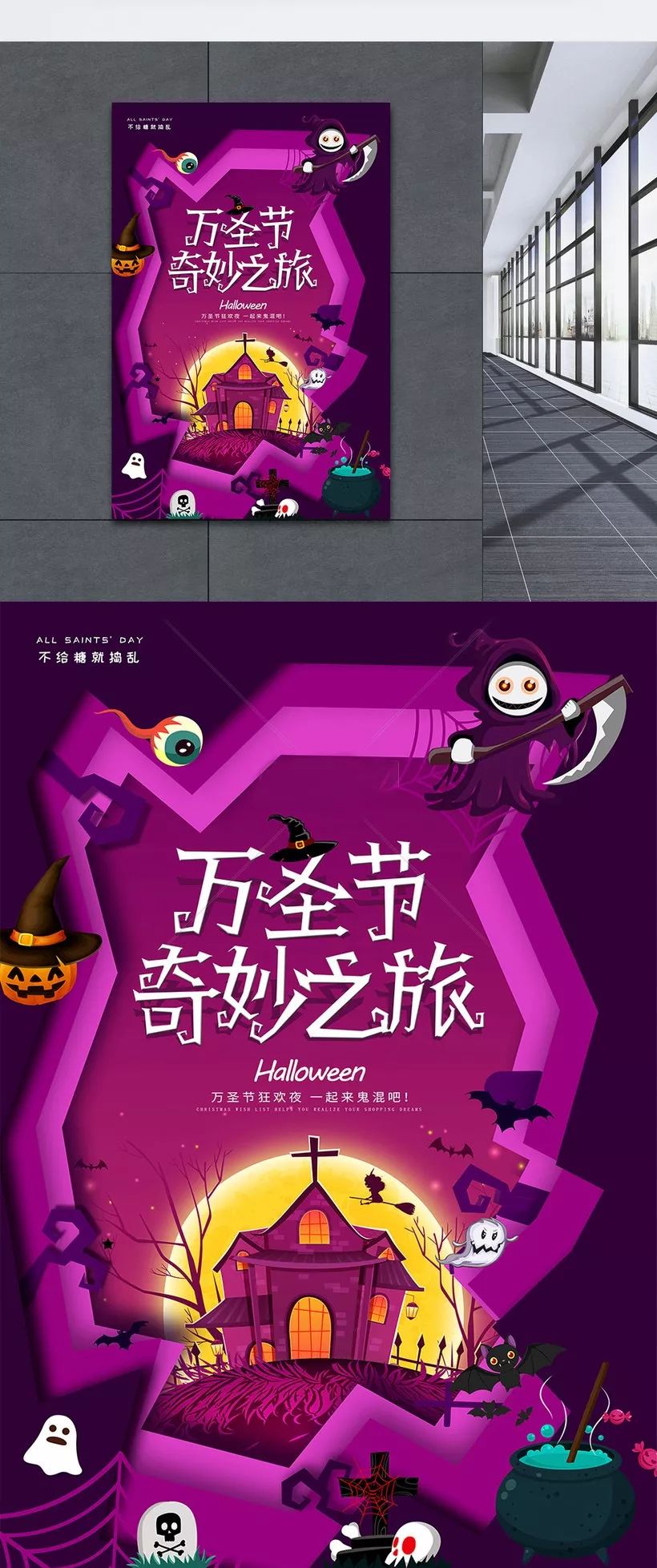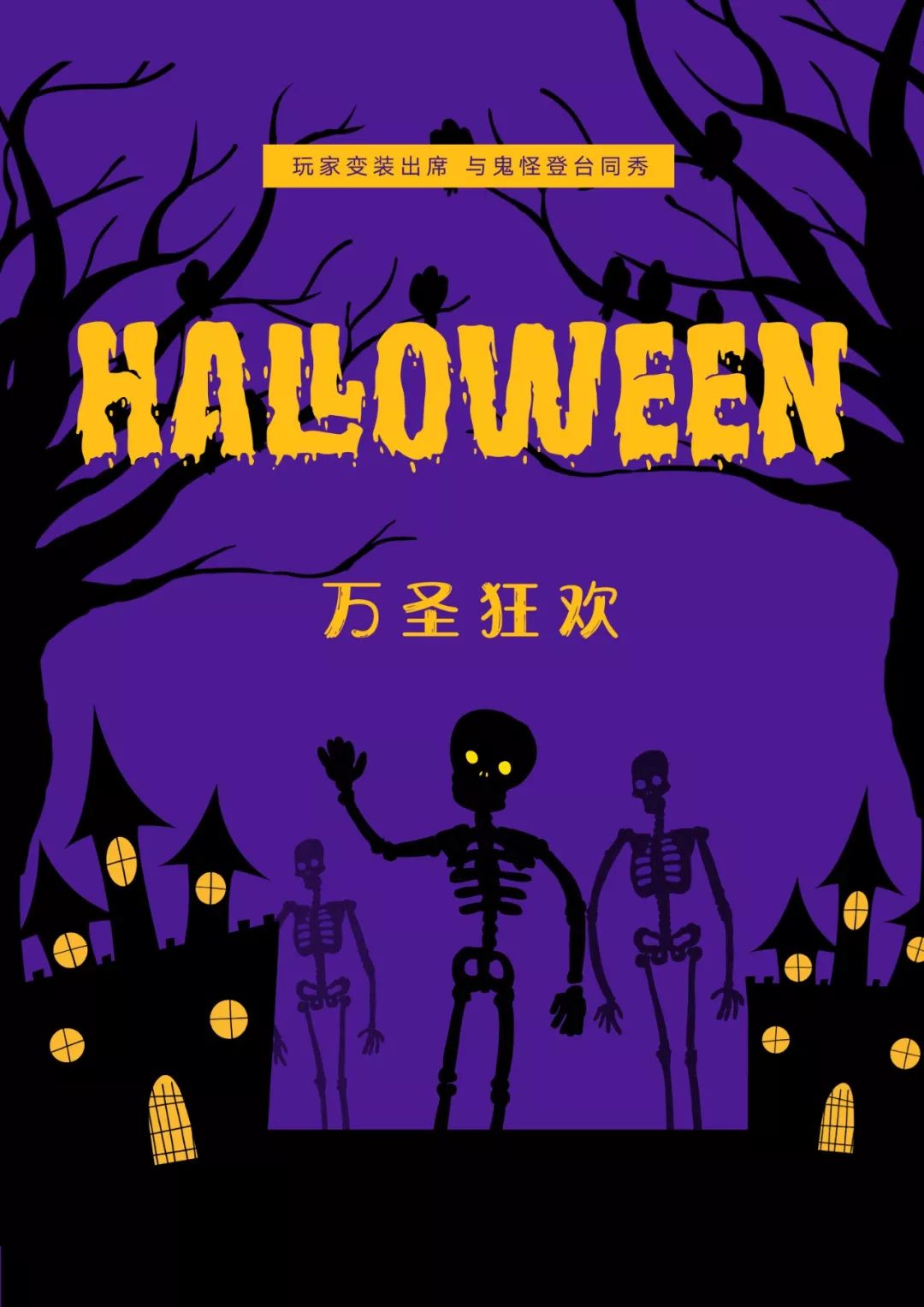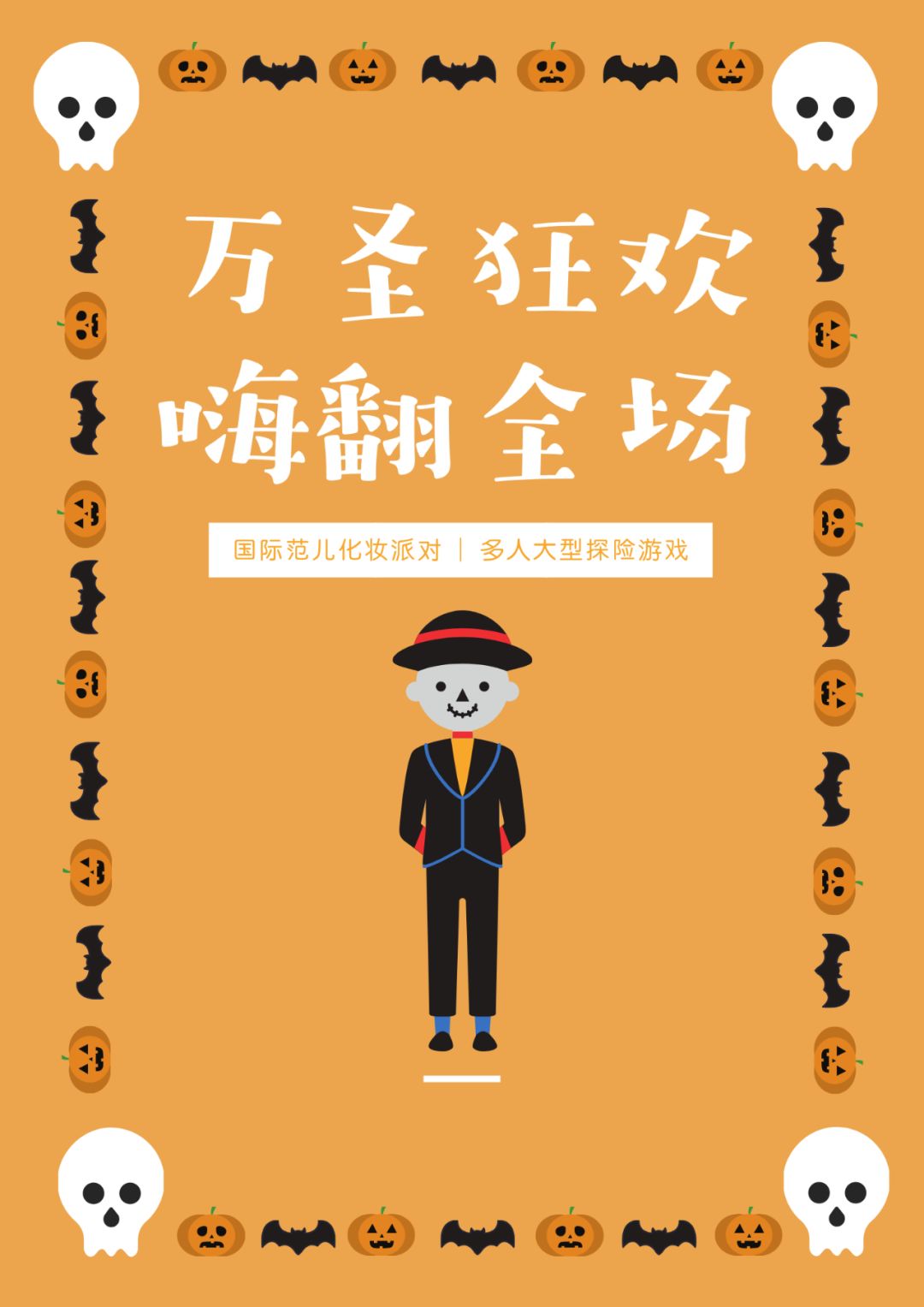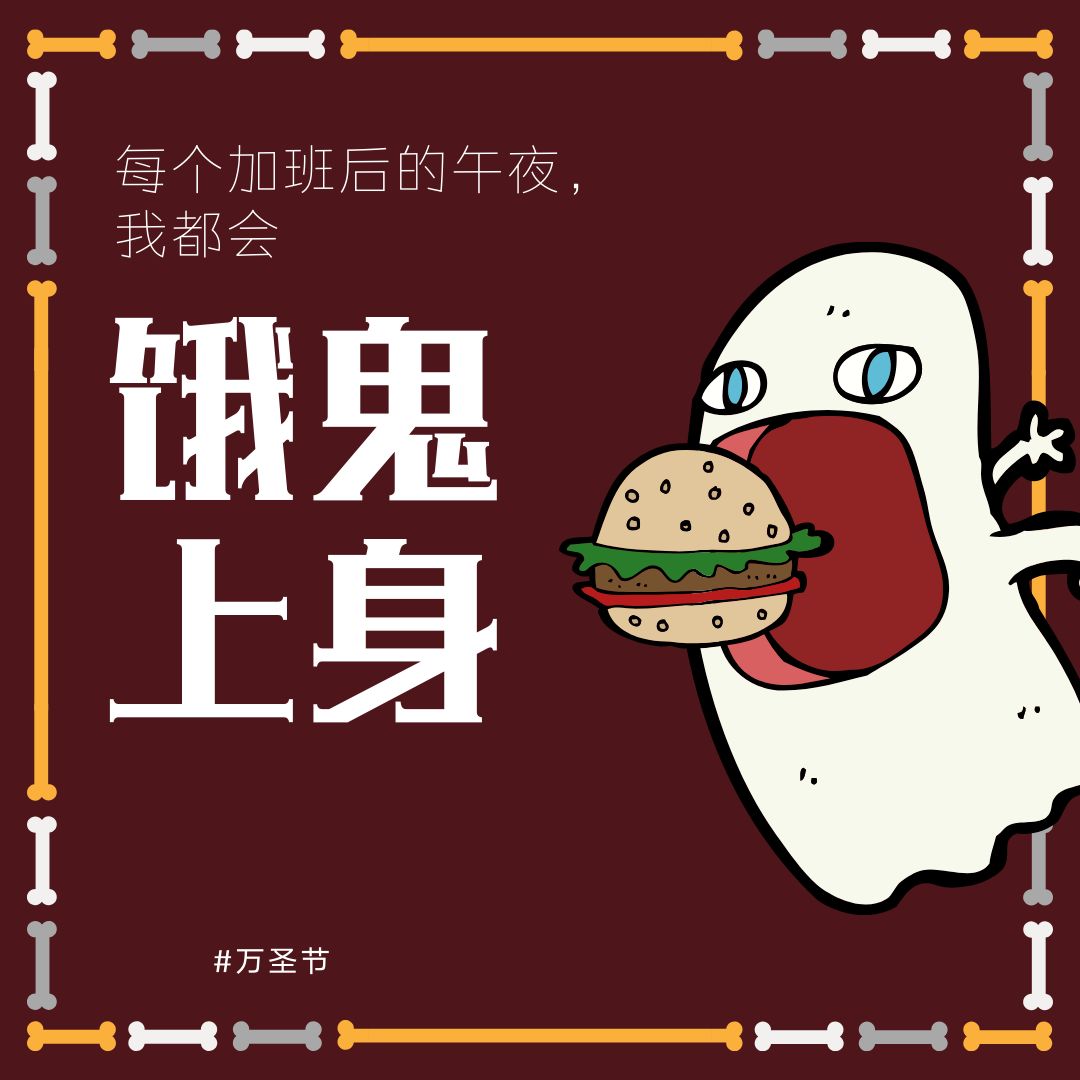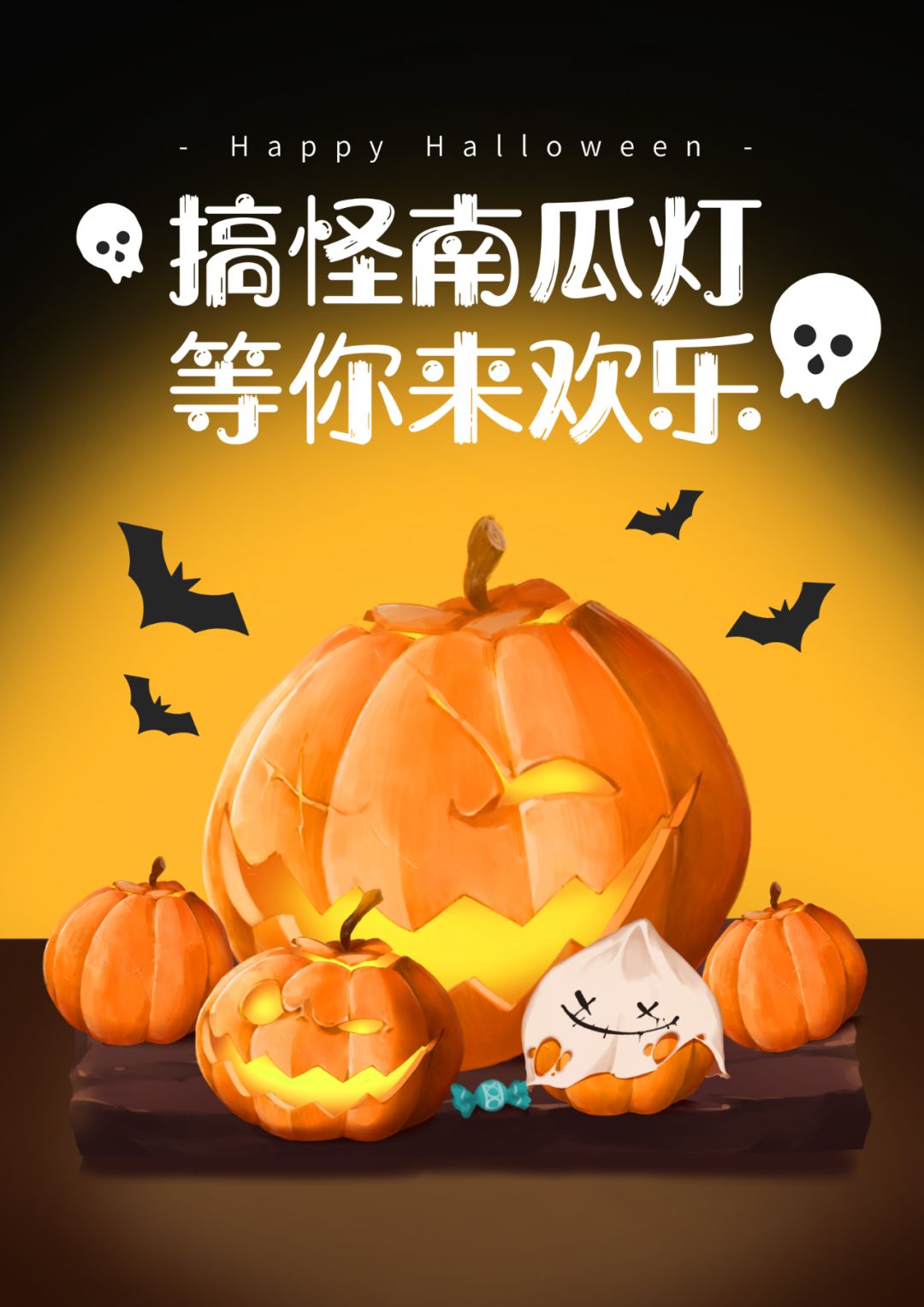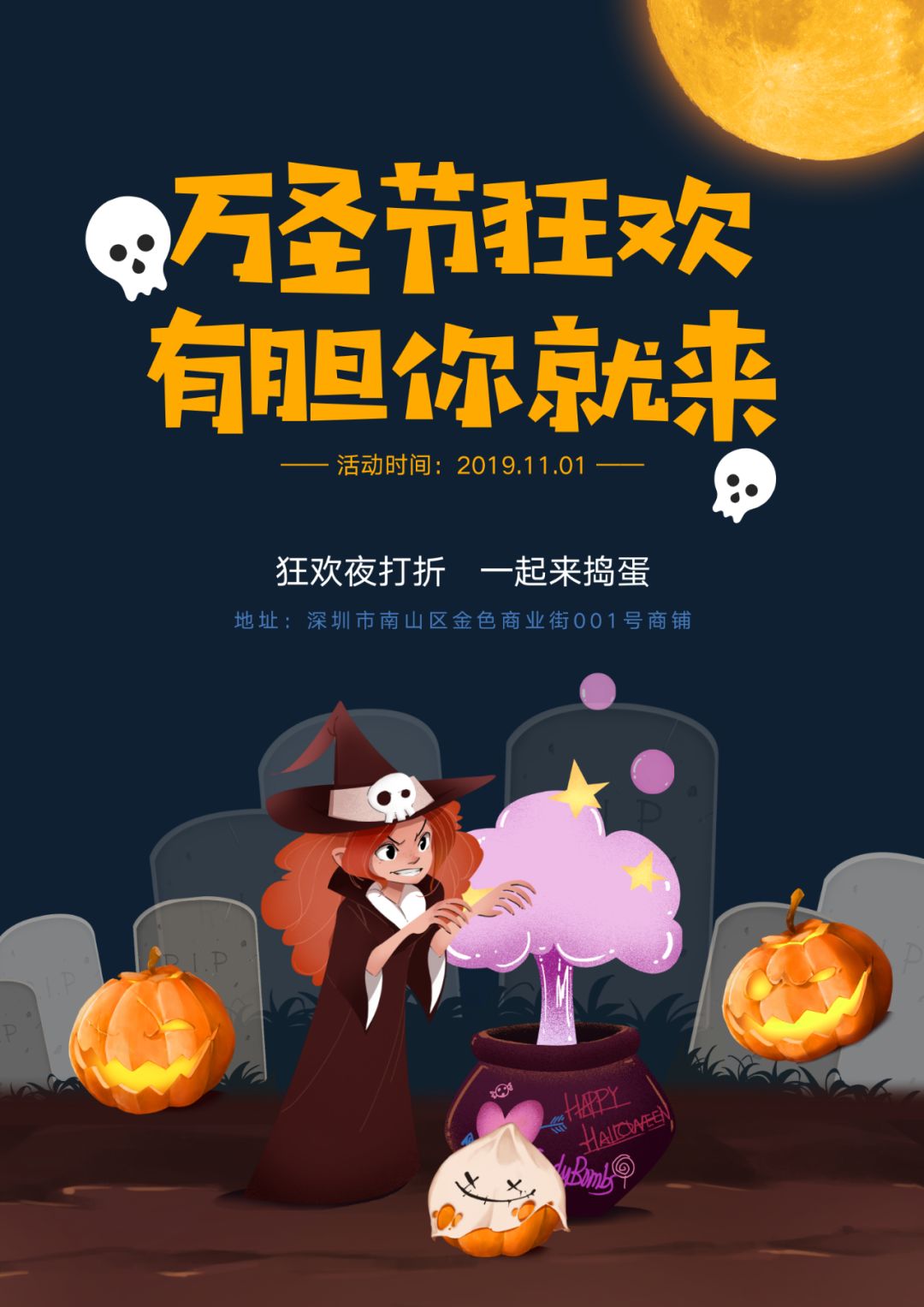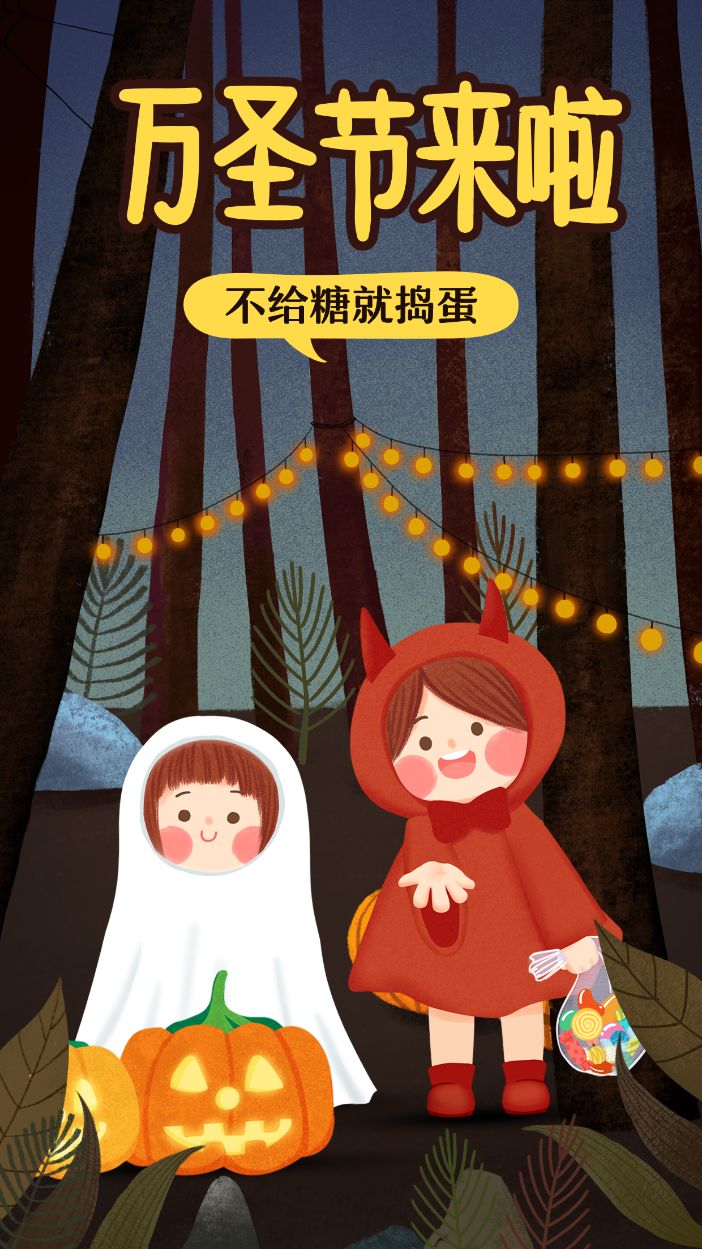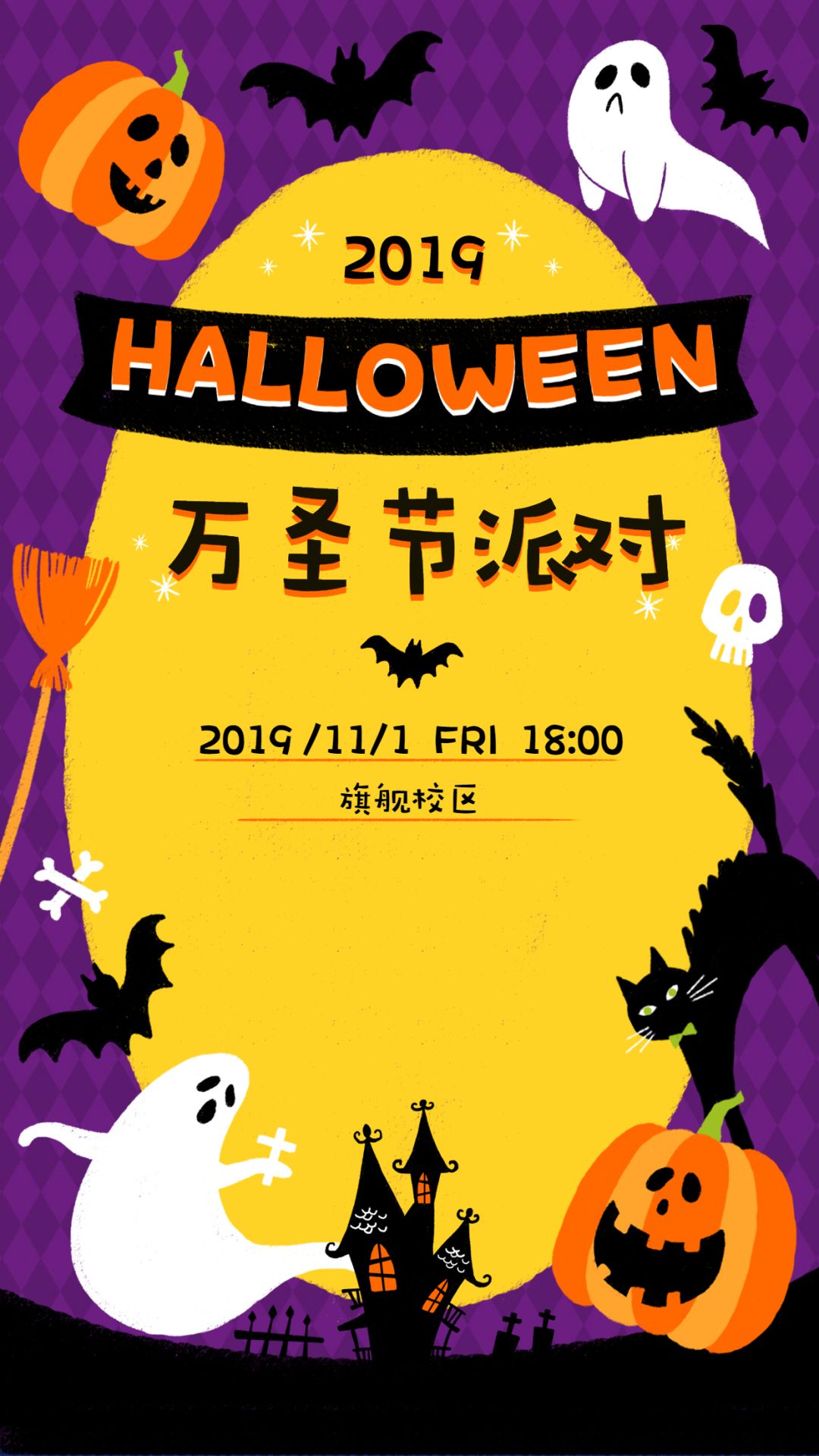
适合万圣节的字体大全,让你万圣节有100种“搞怪”方式
不知不觉,又是一年万圣节了,感觉去年的教程,还历历在目,重新拿过来用也没什么不妥,哈哈~
不过西方对这个节日,倒是蛮重视,柚子10月在北欧的时候,就已经感受到浓烈的气氛了。
特别是那些“搞怪”的字体,很是吸睛,没有它们就称不上万圣节!
万圣节专属
也许是万圣节太独特,还有专门以它命名的字体,别的节日好像都没这个待遇呢……
最近还新上了一款西文,很有感觉,还免费商用哦~
还有几款万圣节的“亲戚”,都是根据元素命名的,看起来很形象。
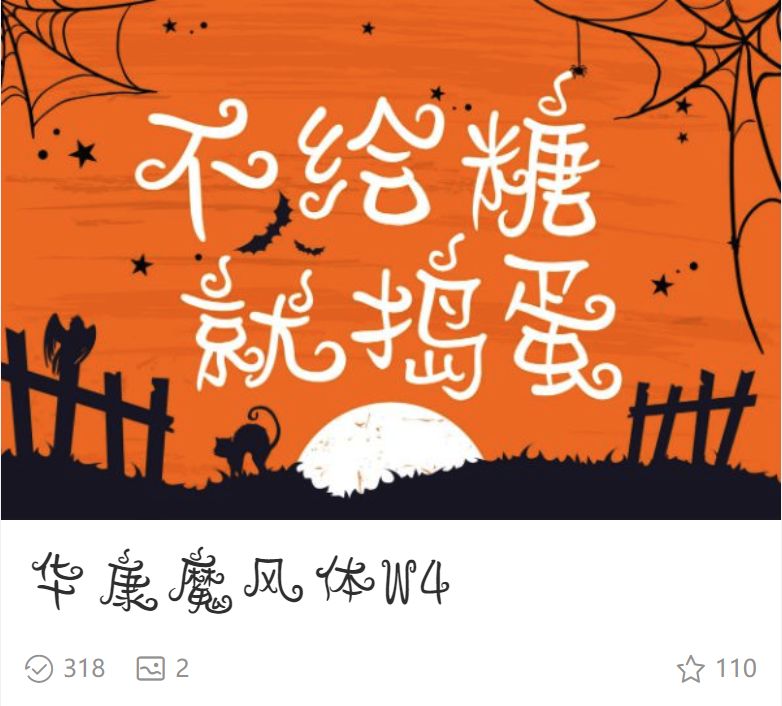
好玩的字体
如果你觉得万圣节,就只能用专属字体,那也太局限了,毕竟你想传达的内容不一样,风格也大相径庭,有些字体,你可能看着不“鬼怪”,但用起来就异常顺滑。
免费字体
前面说了那么多字体,设计师当然还担心版权问题,所以免费字体不可少,我精选了几个适合万圣节的~